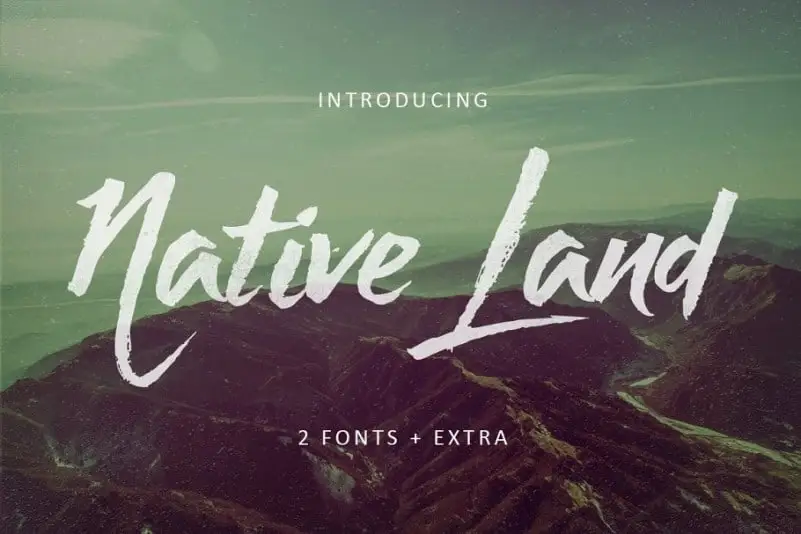
Native Land Brush Font – Download Grátis
A Native Land Brush Font é uma fonte feita para quem busca uma sensação descontraída e criativa. Ela foi desenvolvida pelo Get Studio e apresenta dois modelos de fontes feitos à mão com pinceladas, perfeitos para aqueles que desejam criar designs tipográficos impressionantes em poucos segundos. Esta fonte é perfeitamente adaptada para uso em logomarcas, textos impressos, cartões, rótulos, embalagens de produtos, cabeçalhos e qualquer outro tipo de arte visual onde sua imaginação permitir. O que torna a Native Land Brush Font ainda mais especial é seu estilo aveludado e despojado. Eles foram projetados para se combinar perfeitamente entre si, garantindo que seus textos brilhem sob qualquer luz. Este é um conjunto de fontes perfeito para aqueles que querem dar vida aos designs digitais com uma personalidade única. A Native Land Brush Font oferece uma maneira lúdica e elegante de expressar seu próprio estilo de design, tornando-a a escolha ideal para quem procura adicionar um toque especial em qualquer projeto gráfico.